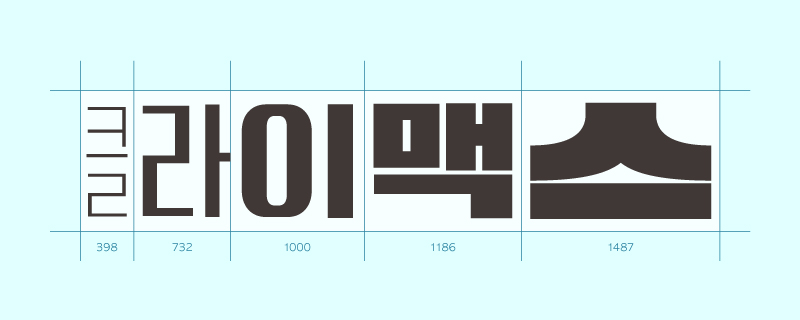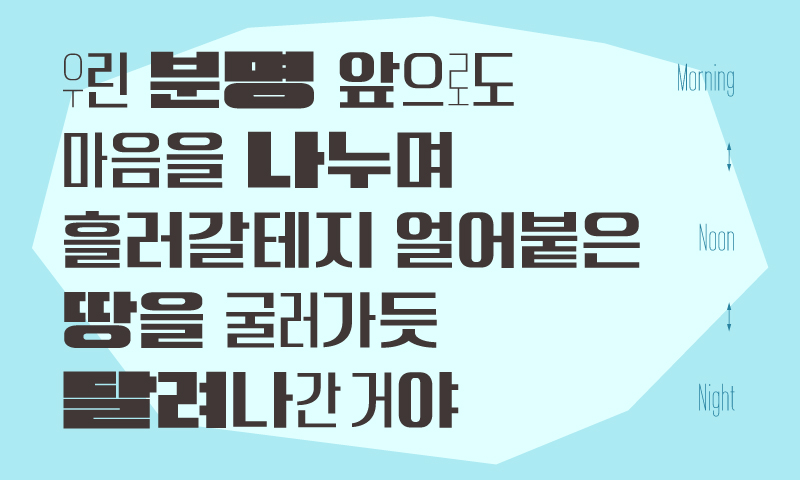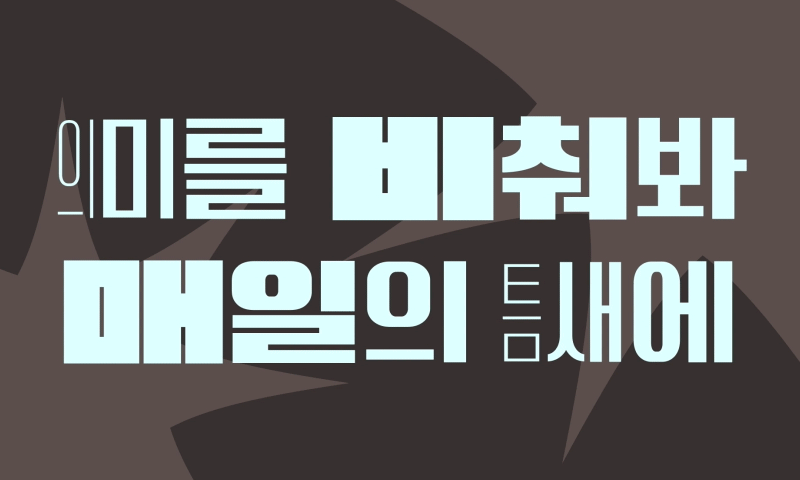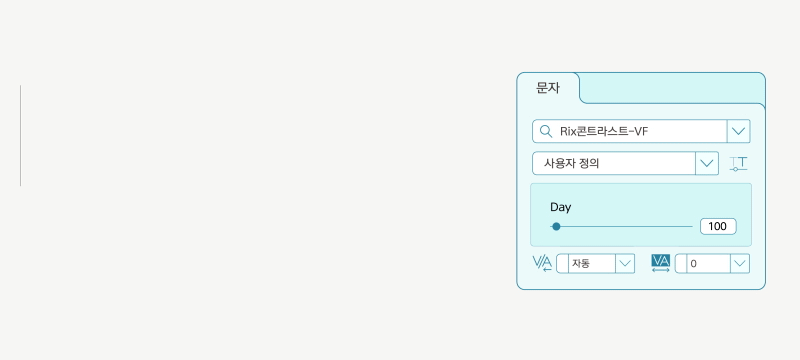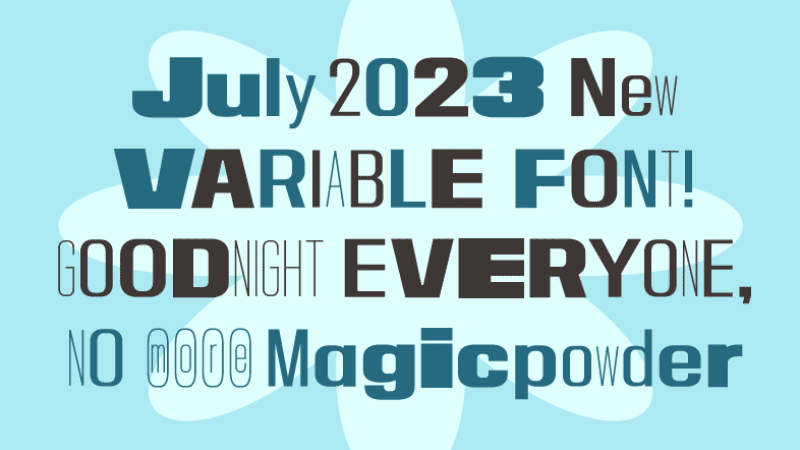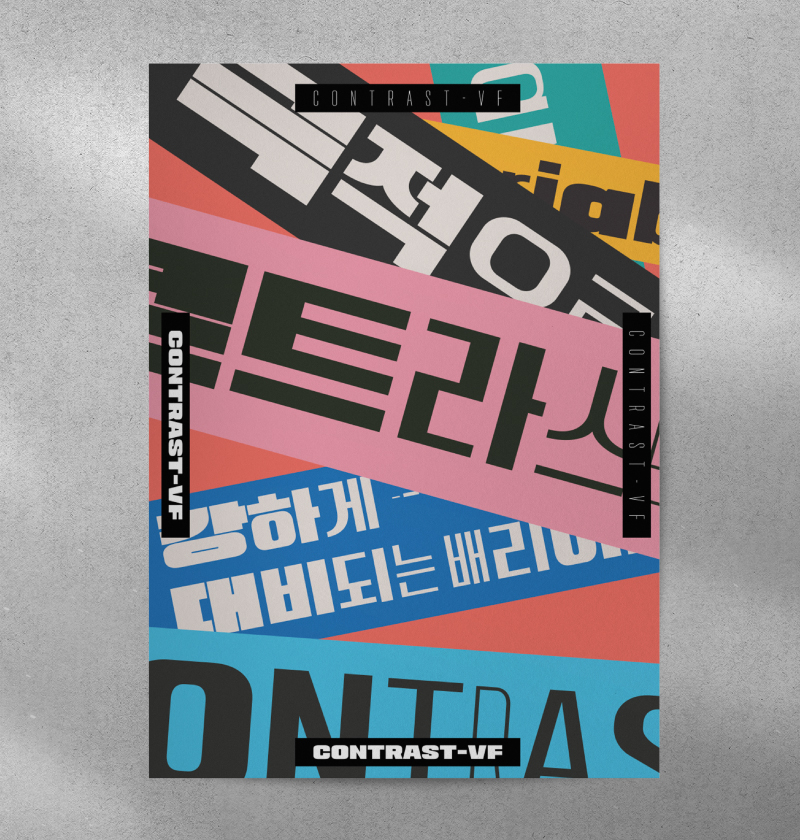
Rix콘트라스트 VF
RixContrast-VF
2개의 시리즈로 구성된 Rix콘트라스트 배리어블 폰트의 오픈타입 적용 버전입니다.
Day 축을 통해 글자의 굵기와 폭이 순차적으로 다르게 나타나는 효과를 조절할 수 있습니다.
한 글줄 내에서 글자들이 좌우로 확장되거나 축소되면서 강렬하고도 재미있는 인상을 줍니다.
| FontFamily | Rix콘트라스트-VF / RixContrast-VF |
| Design | Yun Yu-min, Yu Hyun-Ju |
| Direction | Park Yong-rak |